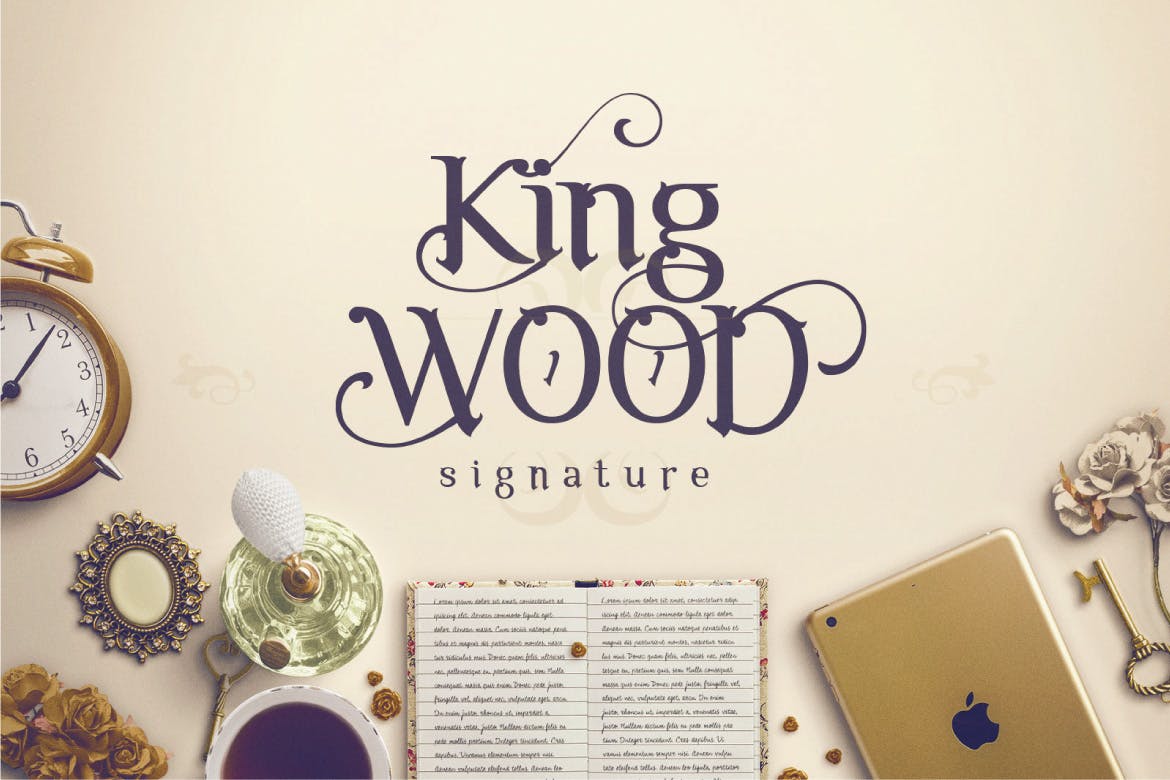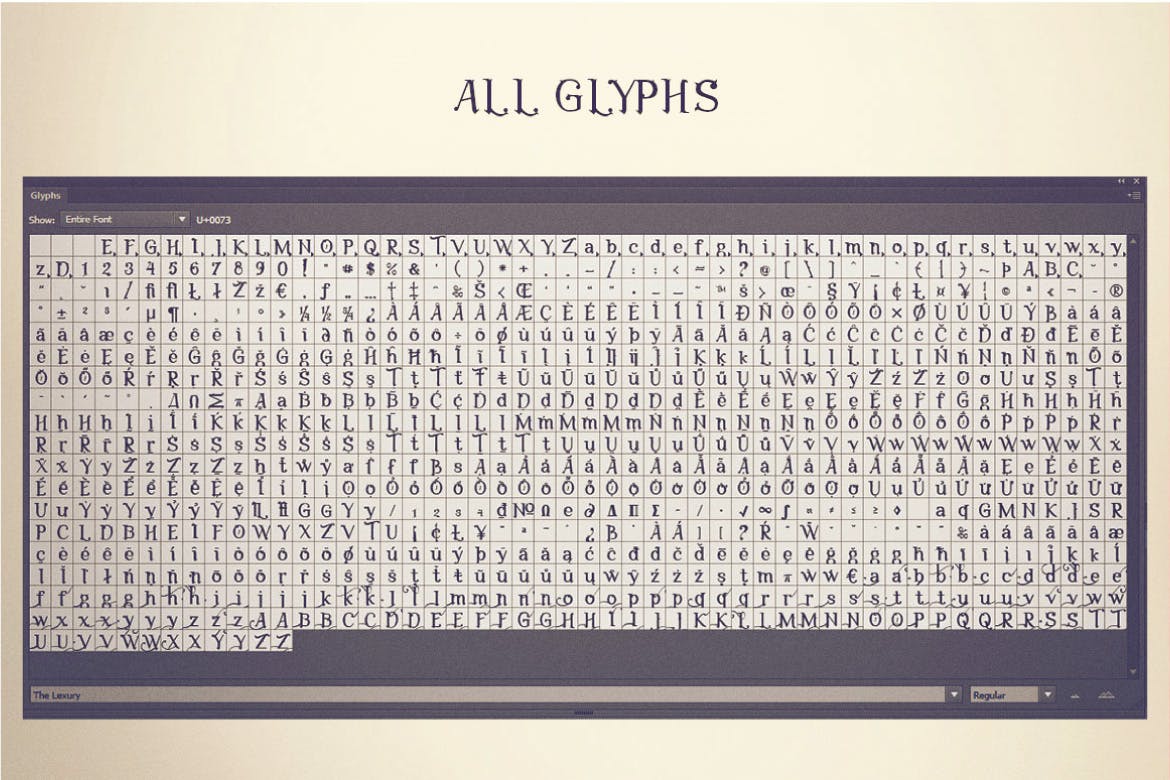
دانلود فونت لوکس و شیک با طراحی منحصر به فرد
The Luxury Elegant Font
این فونت مدرن و وینتج مناسب برای طراحی‌های خاص شماست.
فونت لوکس و شیک یک نوع تایپ‌فیس مدرن و وینتج با کاراکترهای تزئینی و بیس‌لاین رقصان است! این فونت به‌طرز زیبایی در دعوت‌نامه‌ها، کارت‌های تبریک، مواد برندسازی، کارت‌های ویزیت، نقل‌قول‌ها، پوسترها و بسیاری از پروژه‌های دیگر قابل استفاده است.
• طراحی زیبا و منحصر به فرد
• مناسب برای دعوت‌نامه‌ها و کارت‌های تبریک
• قابل استفاده در پروژه‌های برندسازی و تبلیغاتی
• ایده‌آل برای طراحی پوستر و نقل‌قول